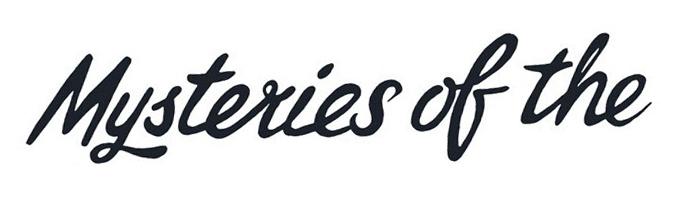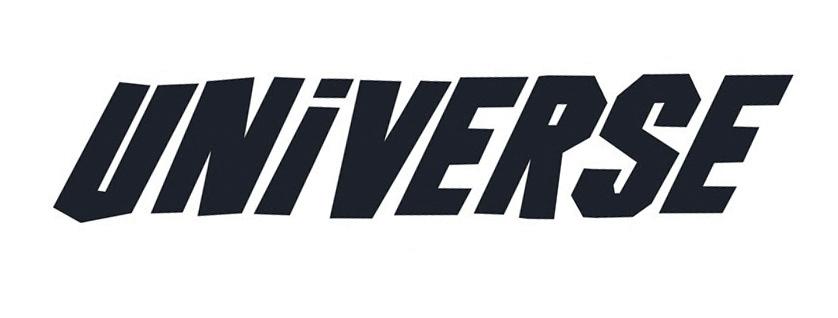
Schriftart von Comic Mysteries of the Quantum Universe
ich suche die Logo Schriftarten vom Comic "Mysteries of the Quantum Universe".
Oben ist eine Schreibschrift und unten eine Comic-Sans.